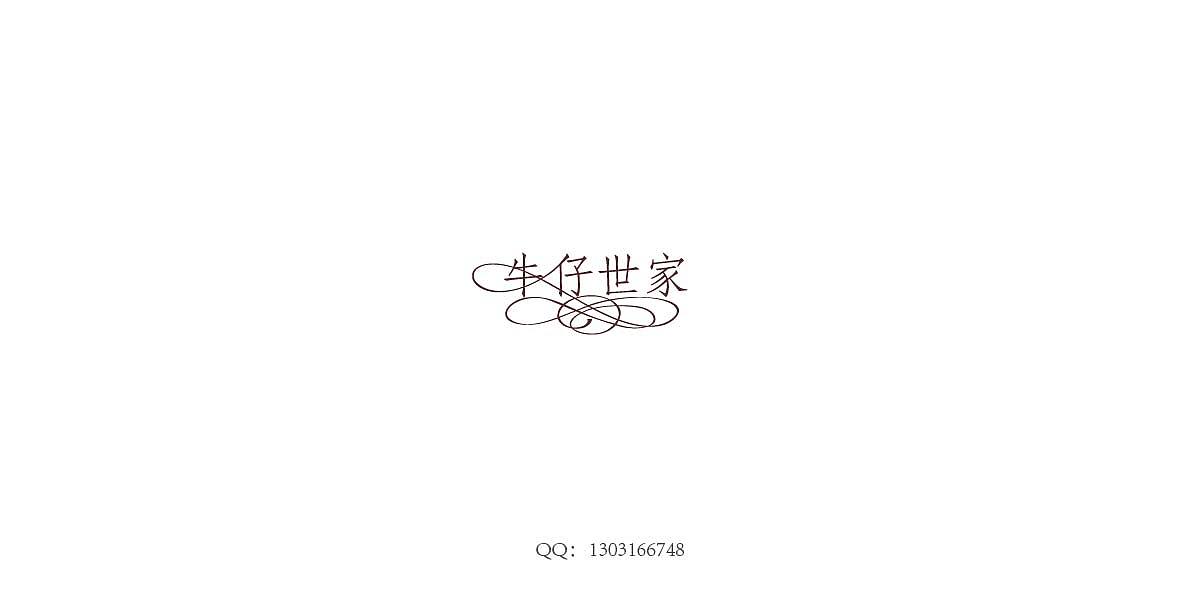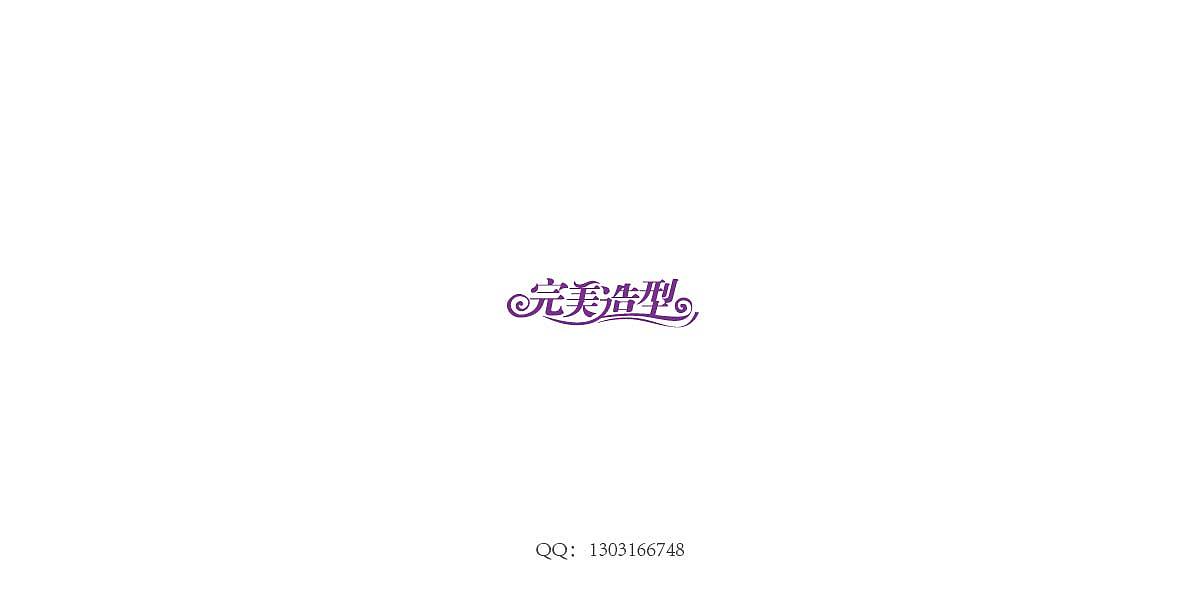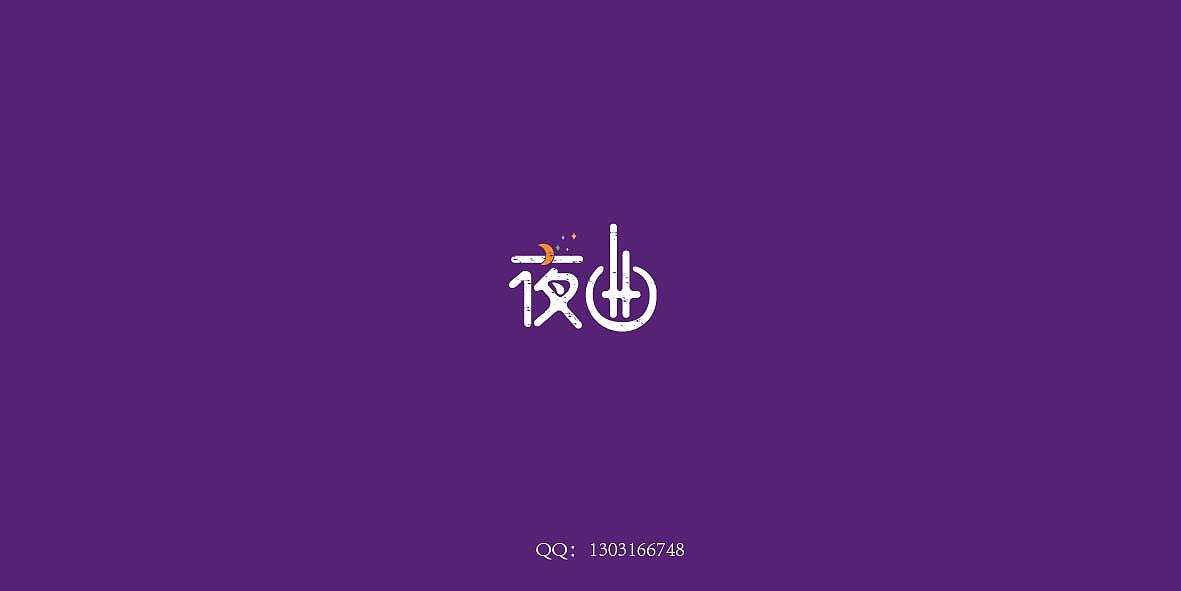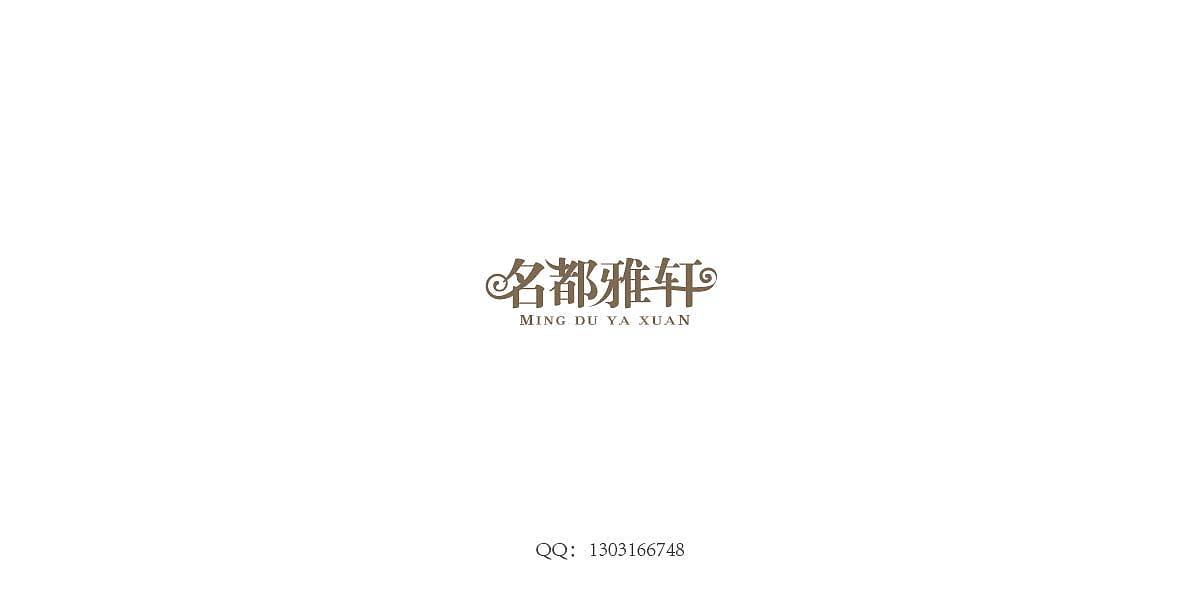
飘带字体设计和一些其他设计
好久没发字体了,最近比较忙,图形logo设计几乎没有发过上来网站,一方面是保护客户的隐私,一方面自己懒得整理。这次发了一些飘带字体设计和一些其他设计,来灵感有欲望,,感觉自己有时候太拼命了,做哪些飘逸字体做个通宵,第二天继续做设计提案,经常昼夜颠覆。
黑白稿。
美丽动人
牛仔世家
金碧怡园
海岸沙湾
完美造型
森林之恋
东方之珠
再别康桥
名都雅轩
城市密码
舞动全城
水岸花园
天使之翼
金碧庭院
聚富餐饮
观云阁
巴蜀烤鱼
夜曲
益生堂
爱上远方的她